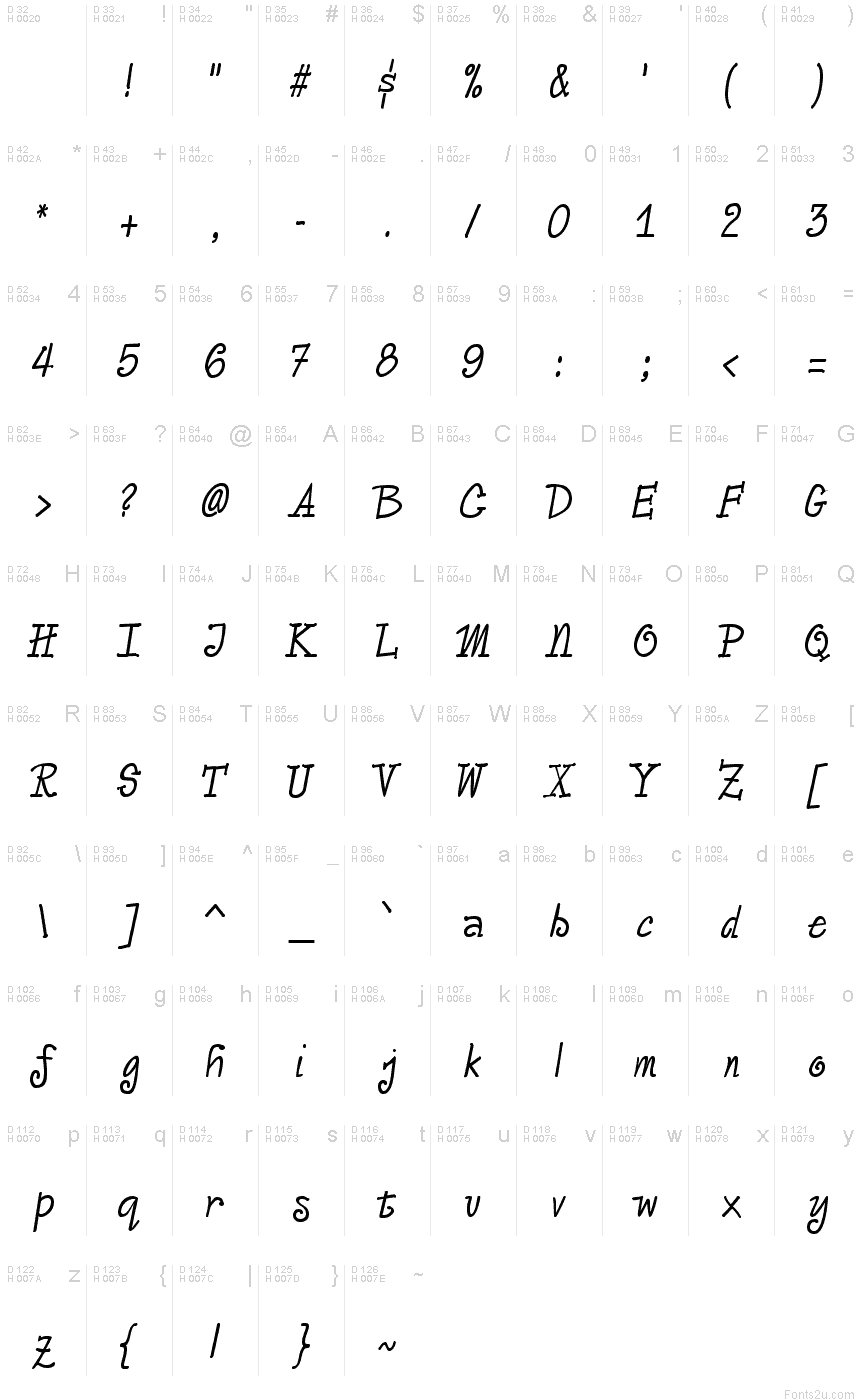
Vassallo autorstwa Jeffa Vorzimmera to darmowy, kręcony krój typu display o żywym, niemal baśniowym rytmie. Litery łączą wysokie, zwężające się pociągnięcia z zapętlonymi zawijasami, a zaokrąglone haczyki w znakach takich jak „a” czy „s” nadają krojowi lekko teatralny charakter w stylu dawnych plakatów, nie stając się przy tym przesadnie ozdobnym.
Dzięki temu świetnie sprawdzi się na opakowaniach butikowych, w menu kawiarnianych, na okładkach książek dla dzieci, plakatach imprezowych oraz w zabawnym brandingu, gdzie tytuł potrzebuje odrobiny polotu. Jako darmowy font, doskonale nadaje się również do krótkich nagłówków, wizytówek i monogramów, ponieważ te zapętlone kształty niosą ze sobą mnóstwo charakteru nawet w kilku literach.